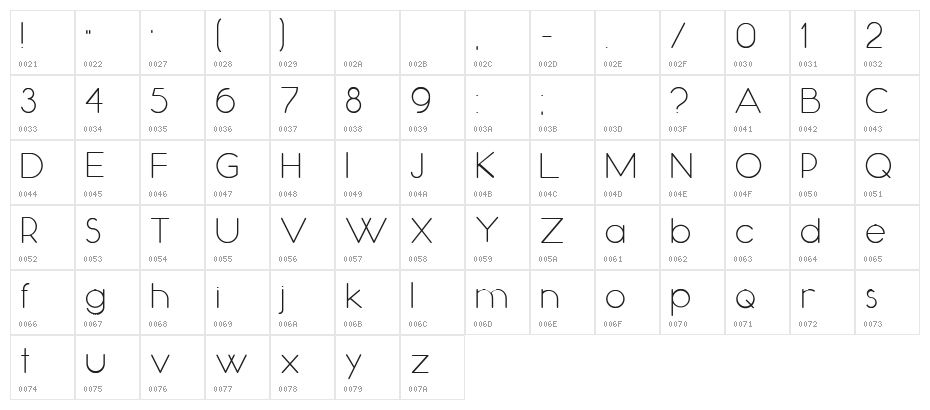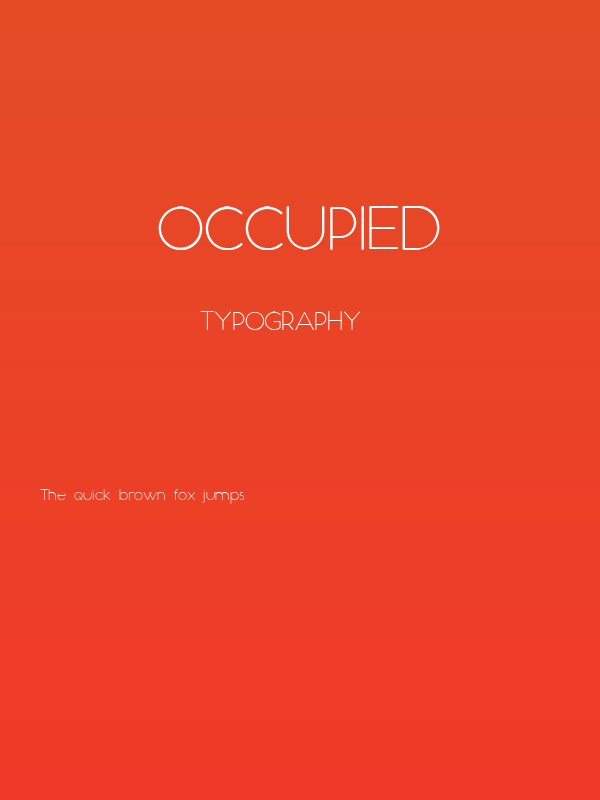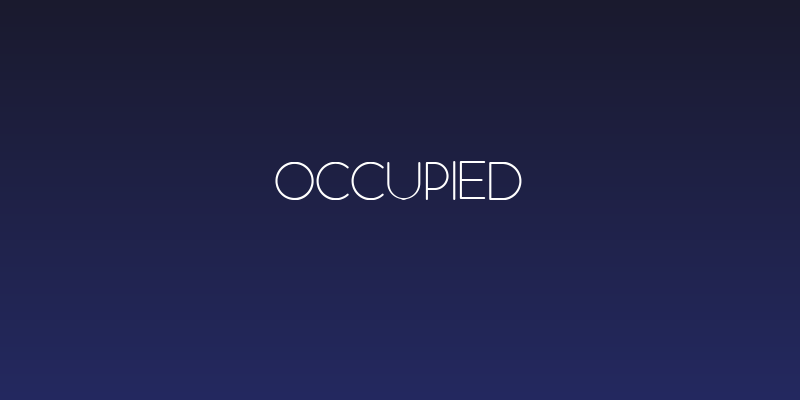
Occupied Font
| Progetti proposti | Ideal for branding, advertising, web design, and editorial layouts where a modern and clean aesthetic is desired. |